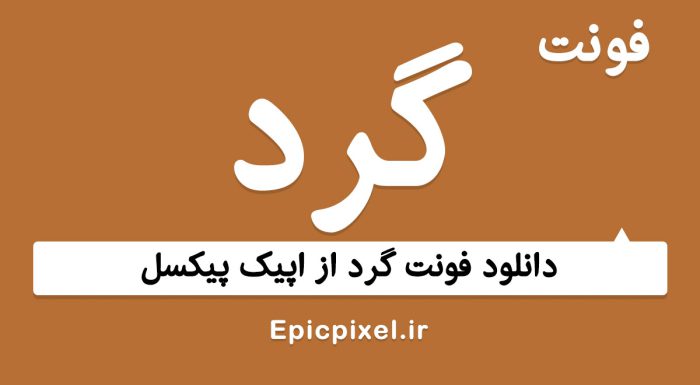
دانلود مجموعه کامل فونت Rounded فارسی Font اپیک گِرد – رُند |
| ⭐ مجموعه فونت | دانلود فونت فارسی اپیک رند اکسترا لایت Font Epic Rounded ExtraLight فونت اپیک گرد لایت Epic Rounded Light فونت روند رگولار Epic Rounded Regular فونت گرد مدیوم Epic Rounded Medium فونت رند بولد Epic Rounded Bold |
| ⭐ توضیحات | مجموعه ای کامل از فونت های گرد و نسخه شبیه سازی شده بنام اپیک گرد یا رند ( شبیه سازی شده از ایران گرد )
فونت اپیک گرد با پشتیبانی از حروف فارسی ، انگلیسی / لاتین ، اعداد فارسی Fu Num بهمراه نسخه وب |